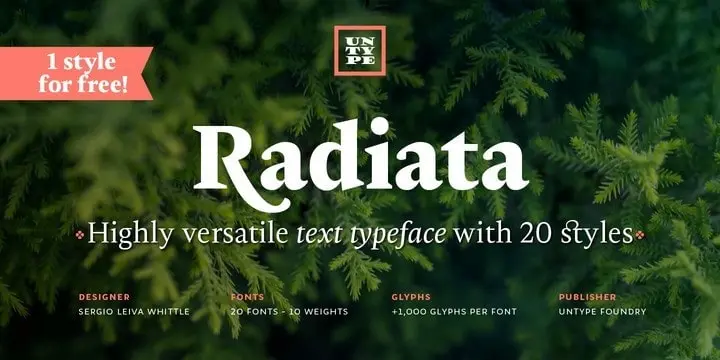
Radiata Serif Font Family
Radiata Serif é uma família de fontes serifadas com estilos modernistas que apresenta curvas únicas e um visual elegante. Desenvolvida por Sergio Leiva Whittle, a Radiata traz uma estrutura robusta combinada com detalhes delicados em suas pontas e pés da letra. Isso cria um equilíbrio entre força e suavidade na composição, introduzindo um ar de racionalidade moderna que se destaca tanto nas configurações padrão quanto nas exibições mais elaboradas. A Radiata é uma fonte perfeita para aquelas produções gráficas que buscam um equilíbrio entre simplicidade e sofisticação, combinando a elegância tradicional das serifas com as modernidades de uma tipografia de estilo moderno. Sua disponibilidade de letras maiúsculas e minúsculas, números e pontuação completa a sua funcionalidade em qualquer projeto gráfico que você possa ter.